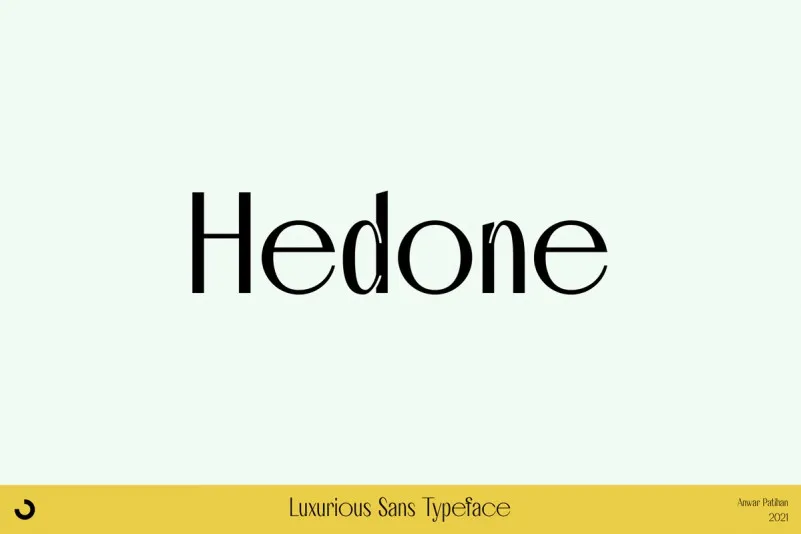
Hedone Font – Fonte Grátis
Hedone Font
A Hedone Font é uma tipografia sans-serif robusta e delicada que traz uma sensação atraente para qualquer projeto gráfico. Seus caracteres têm formas completas, dando à sua escrita um toque elegante e sofisticado. Além disso, o fato de ter pontos de empurrão em cada caractere faz com que Hedone seja ainda mais impressionante e elegante. Este é um grande atalho para aqueles que buscam uma fonte moderna, que pode ser usada tanto no design editorial quanto em artigos de mídia digital ou materiais de marketing. Embora a fonte não tenha características inovadoras na descrição original, ela oferece um aspecto único e atraente, com o seu formato de caracteres completos e os pontos de empurrão que adicionam profundidade à sua natureza. A Hedone Font é perfeita para quem busca uma tipografia moderna e elegante que não fique fora da moda, combinando simplicidade com um toque sofisticado. Ela é especialmente apropriada para designers gráficos ou web que buscam um elemento único para seus projetos.